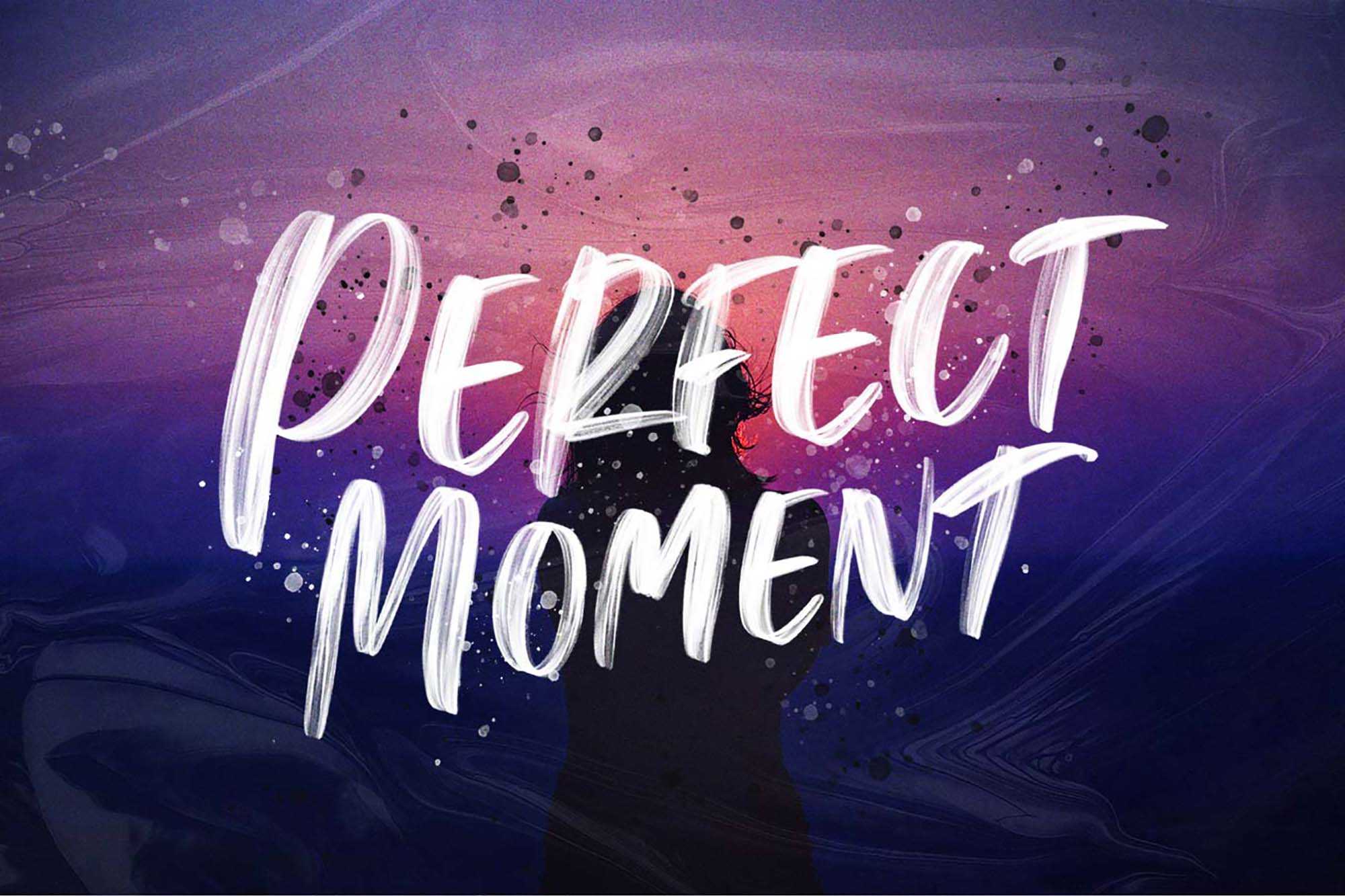
Perfect Moment Handwritten Font – Download Grátis
Descubra a magia de um momento perfeito com o Perfect Moment, uma fonte escrita a lápis. Este é o tipo de fonte criado pelo talentoso Ivan Rosenberg, que oferece um toque moderno e único. Os detalhes elegantes e a simplicidade da escrita a mão trazem um toque especial a qualquer design. Ideal para aqueles que buscam uma fonte única, agradável aos olhos e pronta para uso em poucos segundos. Perfeita para designers gráficos, fotógrafos e qualquer pessoa que deseja dar um toque especial à sua marca ou trabalho. Não deixe de experimentar o impacto de um momento perfeito de sua própria mão.